Web tipográfia egy forró téma, ami azt mutatja, hogy egy ilyen régi kutya új trükköket megtanulni. Míg az internet hemzseg a rengeteg technikai fejlődés az online betűtípus, stílus és trendek folyamatosan változnak. Technikai szempontból nagyon fontos, de néha meg kell nézni a kreatív eleme a dolgokat. Bármilyen fejlett technológia jön az újdonság. Tökéletesítette, nehezebbé válik a használata. Web tipográfia határozottan ment keresztül az ilyen változásokat. Kezdeti visszaélés egyes betűtípusok vezetett tervezők, hogy dolgozzon kreatív döntéseket.
Javasoljuk, hogy megvitassák a különböző trendeket web tipográfia. A példákban már nagyobb figyelmet fordítanak, hogy minden font kommunikál a design, és kevésbé - az építkezés. A kreatív használata a webes betűtípusok nem új, de ez a helyzet minden alapvető eleme a design, hogy van egy pár egyedi célokra.
Nos, nézzük ásni a világ a webes tipográfia.
díszes betűtípusokat
Kezdjük azzal, hogy fontolja meg egy dekoratív font. Azt találtuk, hogy a díszes betűtípusokat általában különböző méretű szívek elismert tervezők. Sokan megvetik őket, mint olcsó, gondatlan és léha, míg mások imádják őket, és használja elég kreatív és érdekes. Nézzünk szembe a tényekkel: mi tartozik a fejlesztők, akik úgy vélik, hogy díszes betűtípusokat gyakran létrehozásához használt nevezhető elleni bűncselekmény design. Mindazonáltal elismerjük, hogy sok tervező használja őket fényesen. Íme néhány példa csak egy erős díszes betűtípusokat
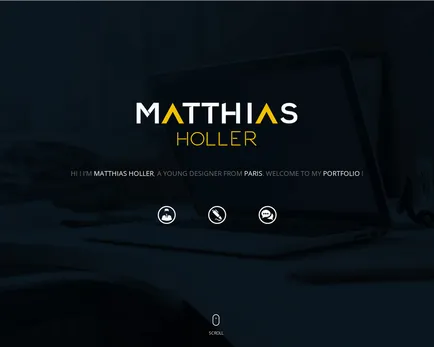
Ebben a példában egy dekoratív betűtípus nem túl stilizált vagy bizarr. Vékony, kis változások teszik egyedivé. A tervező használt betűtípust, hogy hozzon létre egy egyedi stílust, bemutatva azt szinte a logó.
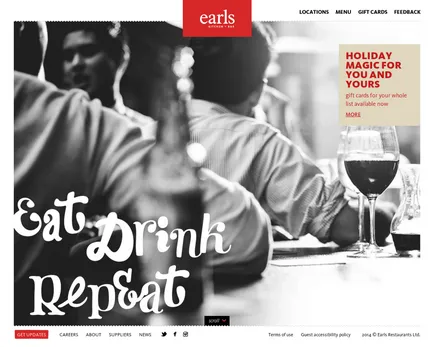
Szemben az előző, ebben a példában egy dekoratív font biztonsággal alkalmazható, és az úgynevezett „fej”. Ez az a technika segít létrehozni egy merész és egyedi stílusát a konyhában található.
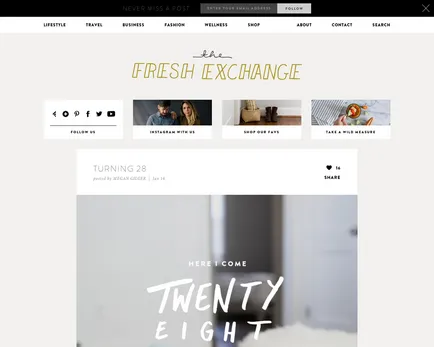
Ez a honlap a váratlan sor díszes betűtípusokat közvetíteni csípő stílusú design. Ez merített. Hipster stílus nagyon népszerű a kölcsönhatás a fiatalok közönséget.
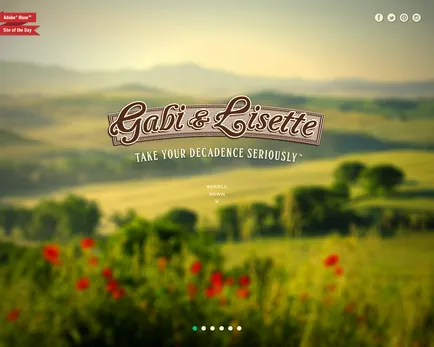
Ez a szórakoztató tervezési mutat egy pár nagyon stilizált betűtípusok, hogy megtalálja a csomagoláson az élelmiszerek az interneten. Ennek használata segít beállítani a webhely tervezési egy bizonyos hangot, és tökéletesen kiemeli a márka.
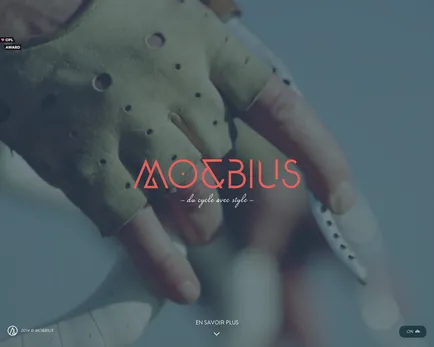
Minták, mint ez, azt mutatják, hogy még a leghihetetlenebb betűtípus helye van web design. Ez csodálatos példája tökéletesen illusztrálja ezt az állítást.
húzott betűtípusok
Húzott betűtípusok régóta része a web design. Néha tényleg rajzolt betűtípus, amelyet ezután ellenőrzi, de sok esetben ezek a betűtípusok néz ki, mint csak festett. Előnyösen persze, úgy néz ki az eredeti, kézzel rajzolt szöveget, de néha a szerkesztett példányt a betűtípus néz ki. Mindkét joga van az élethez. Nézzünk néhány példát a helyszínek, hogy használja ezt a stílust.
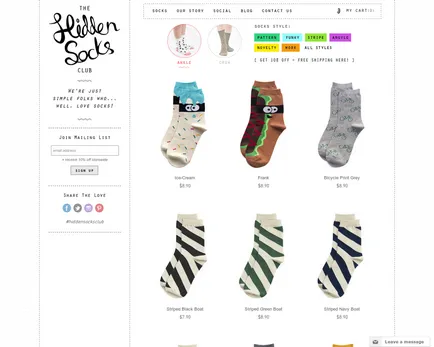
Ez az e-kereskedelmi webhely használ rajzfilm szöveg tükrözi a tulajdonságait a márka fő termék. Ő tökéletes harmóniában van kötés zokni, hogy ténylegesen értékesítik az oldalon.
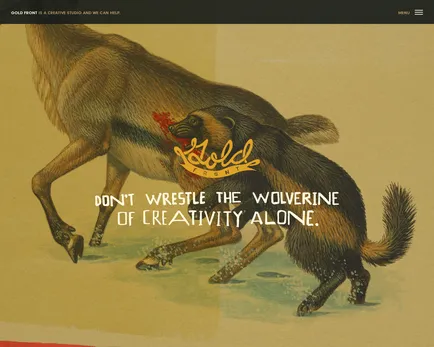
Ebben a design, kézzel írott betűtípust használ, hogy tükrözze a szervezet, amelynek honlapján látunk. Művészi gyökerek a design ügynökség süt át a szokatlan design a fő oldalon.
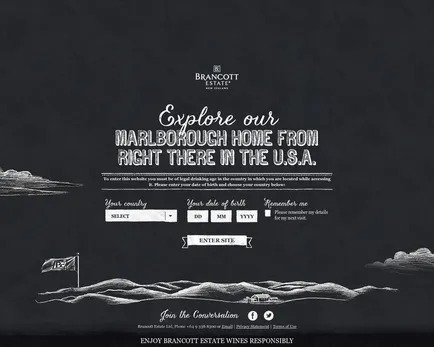
Ezen a honlapon megtalálható egy érdekes kombinációja az úgynevezett pszeudo-script, azaz arról, hogy úgy nézett ki, mint egy festett. Gyakran úgy néz ki, olcsó, de ebben az esetben az eredmény tökéletes a márka.
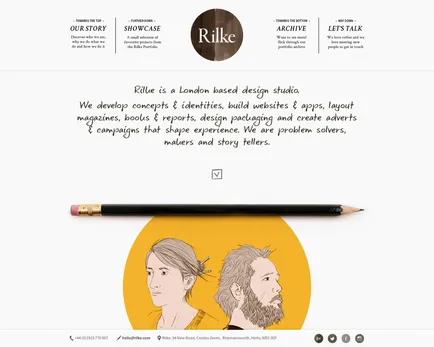
Mivel gyakran előfordul, az oldal használ egy kézzel rajzolt szöveget tükrözik az elvégzett munkát a társaság. Amikor a stílus egyértelműen kapcsolódik az üzleti, mint a választás úgy érzi, kényelmes és nyugodt.
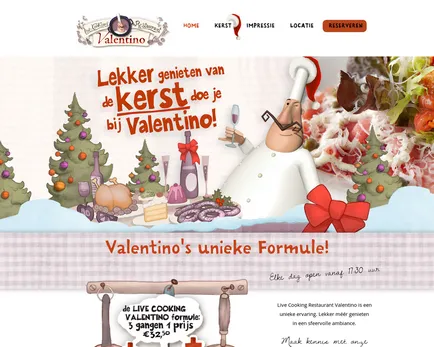
Ellentétben a korábbi példákat, ez egy élénk példája annak, hogy a használata kézzel rajzolt font rezonál, és létrehoz egy egyedi stílusban. A használt betűtípus, hogy erősítse a márka és természetes része a teljes design.
födém serif
Ez a példa jól szemlélteti, hogy az alakja betűk lehetnek gyönyörű önmagában. Nem sok ez a kialakítás modell, mégis beszél kötetek. Valamint bemutatja butikok mutatják a fogyasztó a magas színvonalú, ez a minimalista web design növeli a felfogást, a márka prémium és meghatározza a magas elvárások a látogatók számára.
Szemben az előző, ez a kialakítás - játékos és szórakoztató. Itt födém serif úgy érzi, több divatos és kevésbé súlyos.
Slab serif serif tűnik a leggyakrabban használt nagyobb képernyők. Ebben a konstrukcióban a figyelme csak kisebb szöveg méretét. Sűrű és zömök, ő határozza szép ritmus, ami felemeli az egész struktúra egészére.
Tervezési módszer, amikor egy szűk script, helyezzenek el egy szűk kör, balra tolódik, úgy néz ki, különösen érdekes. A fennmaradó körök jelenik meg az oldalon, csak a vastagsága a fő sejt stressz. Általában ezek a szabványos elemeket keresni elég elegáns.
És ez a szép design egyesíti a három teljesen különböző betűtípust létrehozni egy elegáns képet. Monogram vált logó, és a környező betűtípusok csak segít, hogy kitűnjön.
Az utolsó példa olyan módszert használ figyelembe vett nekünk egy nagyon érdekes módon. Keverés betűtípus ebben az esetben - csupán egy példája, ami növeli a szépség a teljes design. Betűtípusok tökéletesen együtt műalkotások és tükrözik az ugyanabban a stílusban, mint a többi site design.